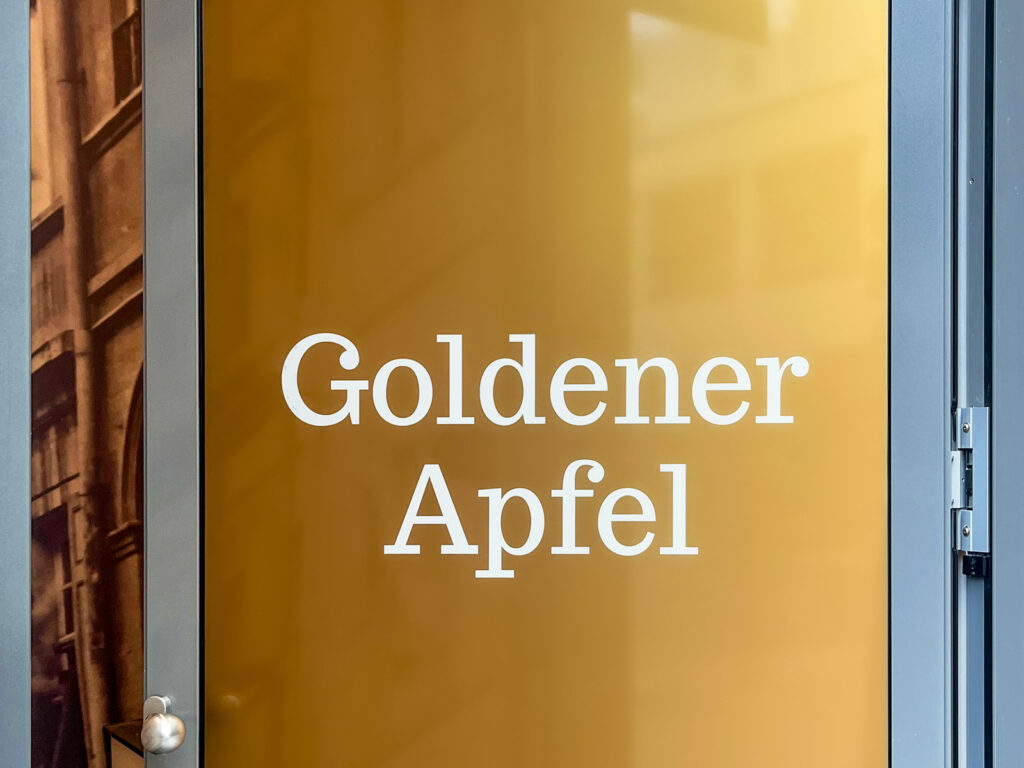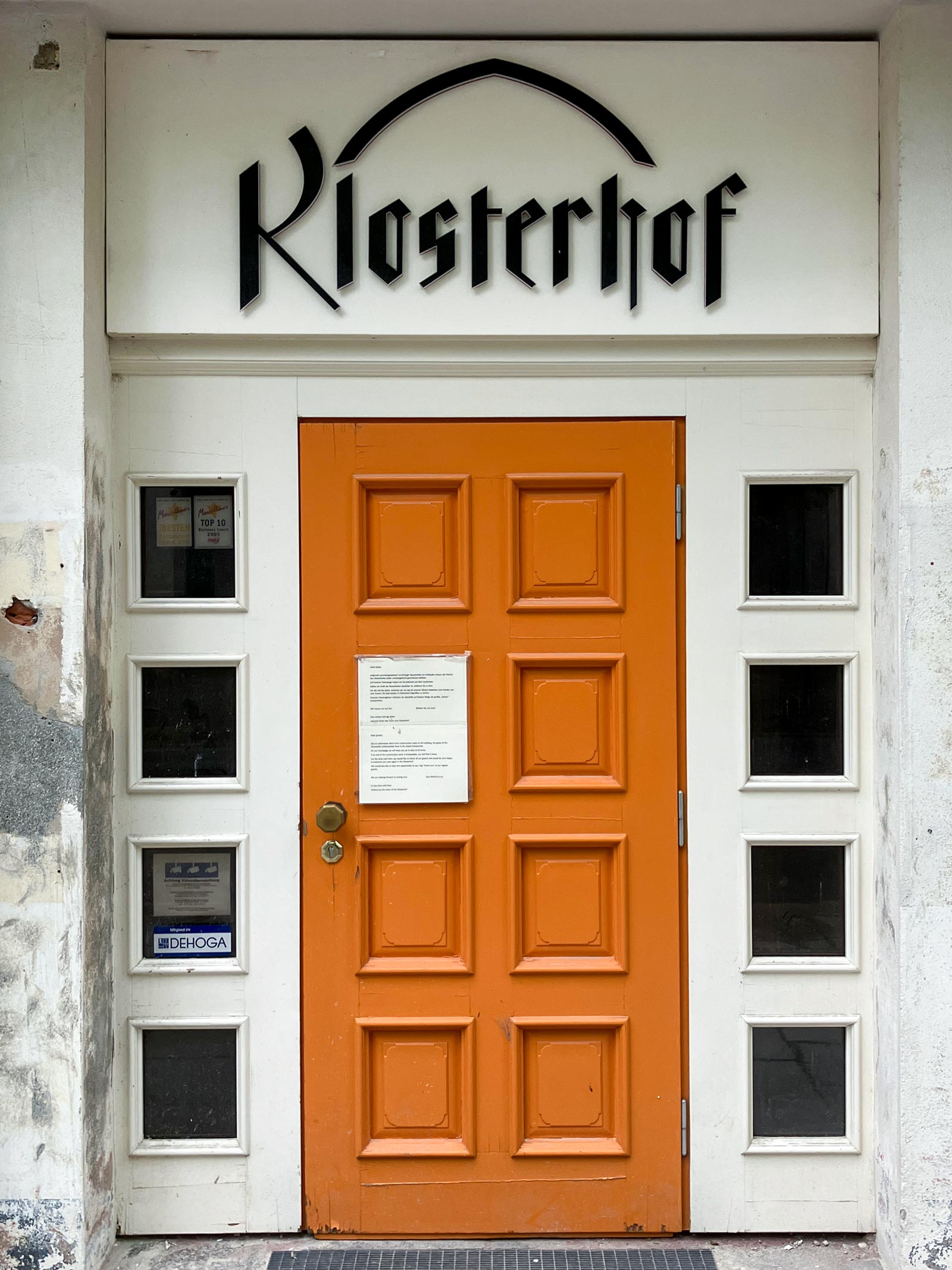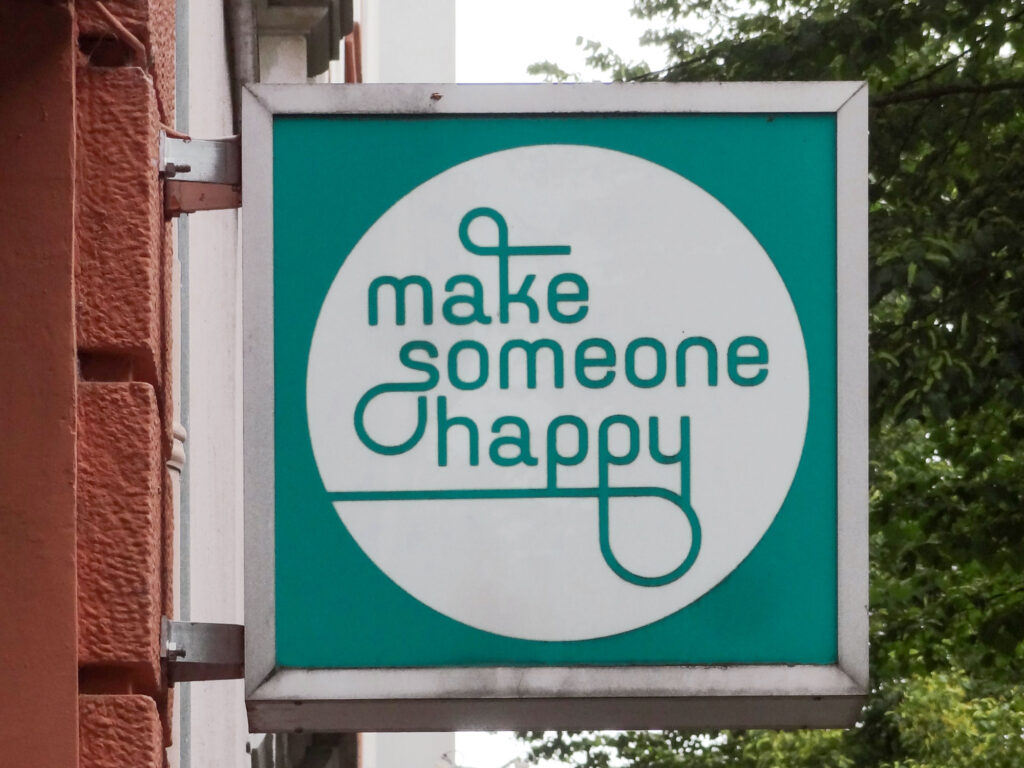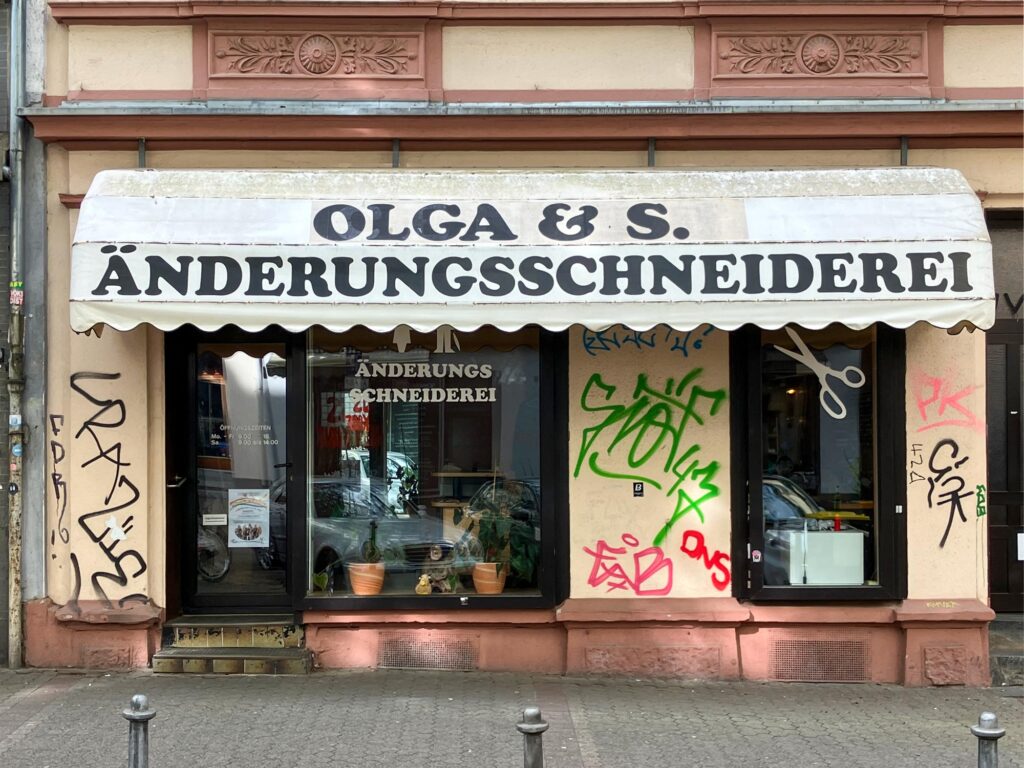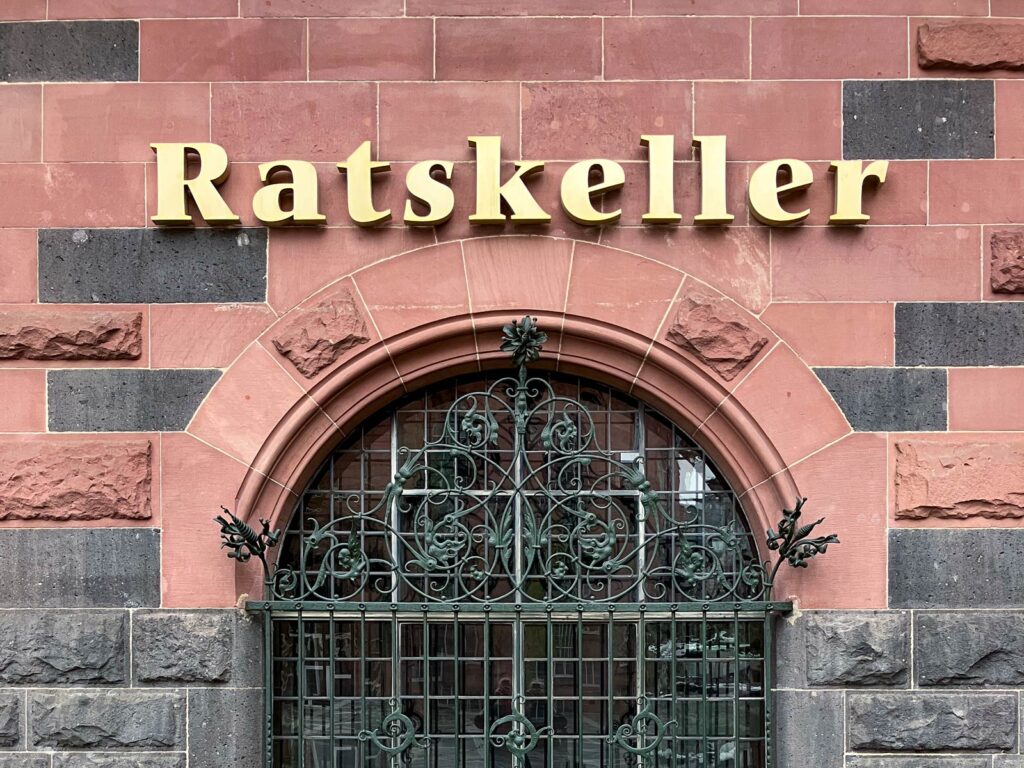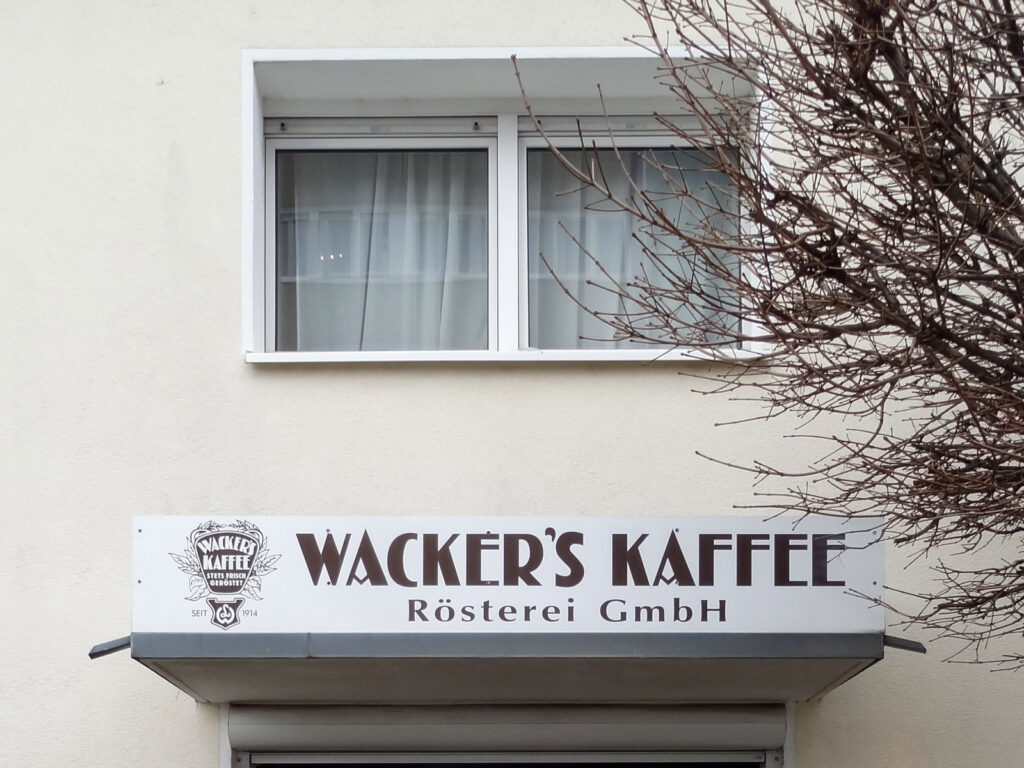
Seit nunmehr 12 Jahren präsentiert die Reihe Typografie in Frankfurt eine fotografische Übersicht von Schriftzügen im öffentlichen Raum, die funktionale und ästhetische Aspekte der Typografie widerspiegeln. Diese Schriftzüge werden überwiegend für Einrichtungen aus den Bereichen Kunst, Kultur, Gastronomie und Dienstleistung verwendet. Ob serifenlos oder serifenbetont, einfarbig oder bunt, geometrisch konstruiert oder gebrochen – auch im 13. Teil dieser Reihe wird wieder eine große Vielfalt abgebildet.
Typografie in Frankfurt (13)